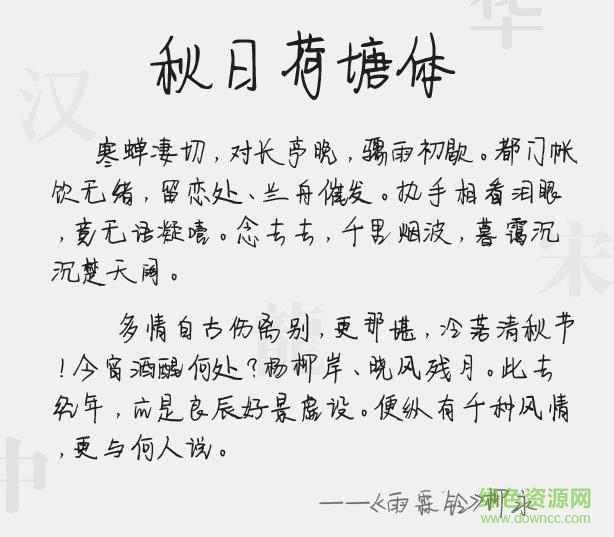
秋日荷塘體字體ttf能夠?yàn)橛脩魝儙硎謨?yōu)美的字體體驗(yàn),這款字體中蘊(yùn)含了大量的獨(dú)特字體效果,每一個(gè)字體都像是手寫而成,擁有獨(dú)特的瀟灑風(fēng)格,給你優(yōu)質(zhì)體驗(yàn)!
這款字體能夠讓你實(shí)時(shí)都體驗(yàn)到不錯(cuò)的視覺效果,精美異常,讓你感受到獨(dú)特的風(fēng)格,在各類寫作以及媒體制作中都將帶來意想不到的妙處!
字體簡介秋日荷塘體字體是一款適合鋼筆書法書寫的字體,由綠色資源網(wǎng)素材整理發(fā)布,提供最全最新中英文字體素材。